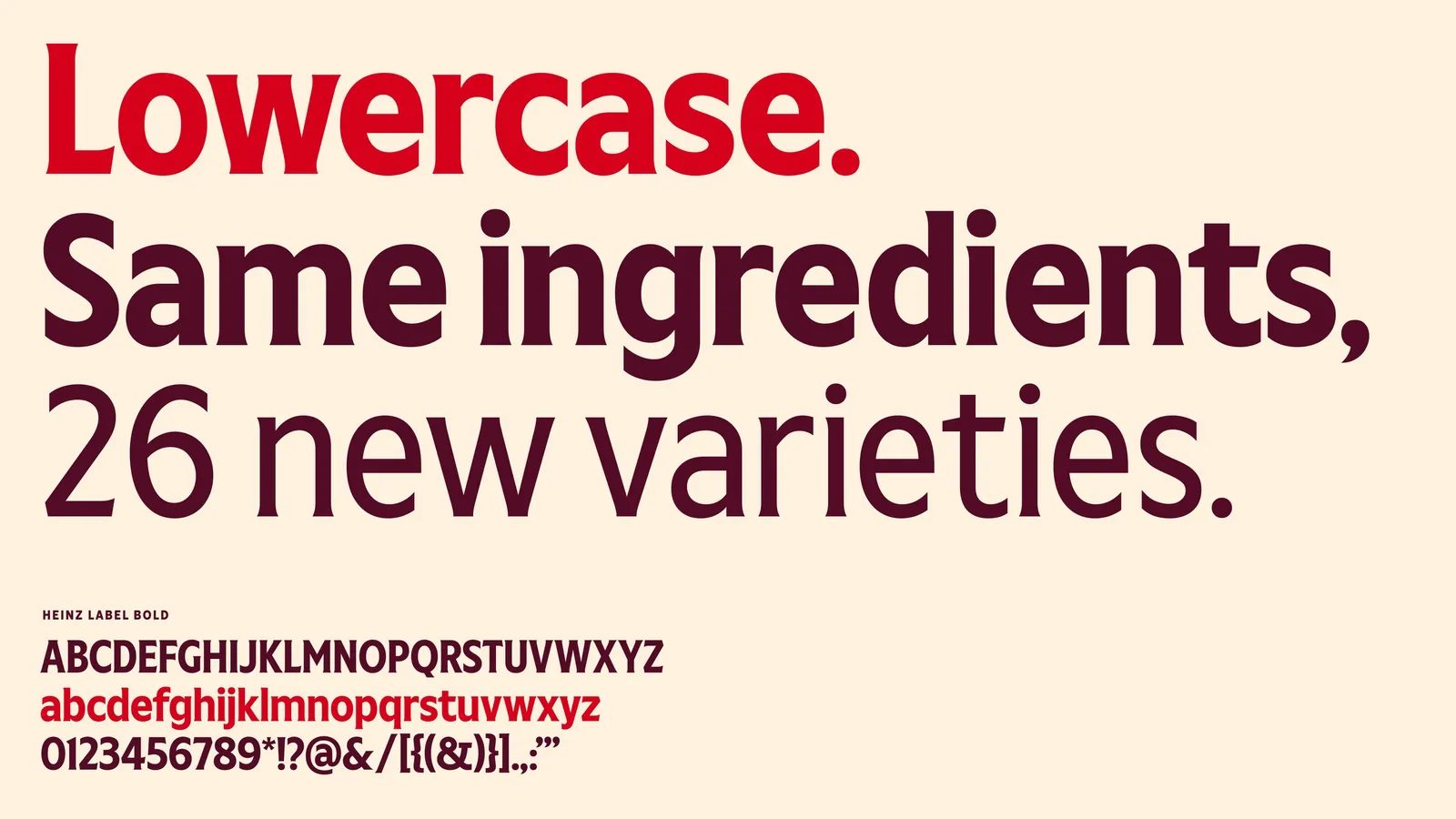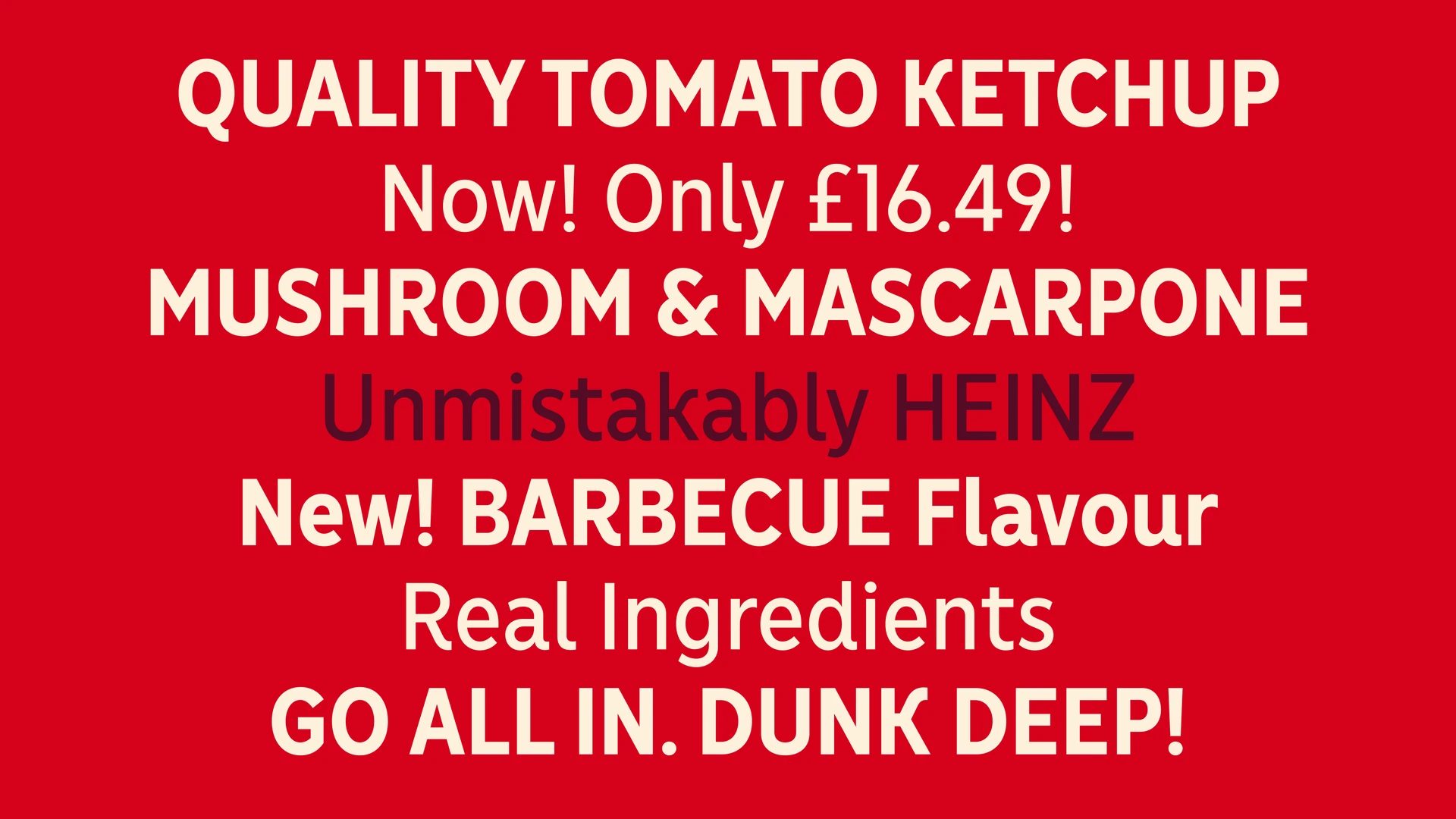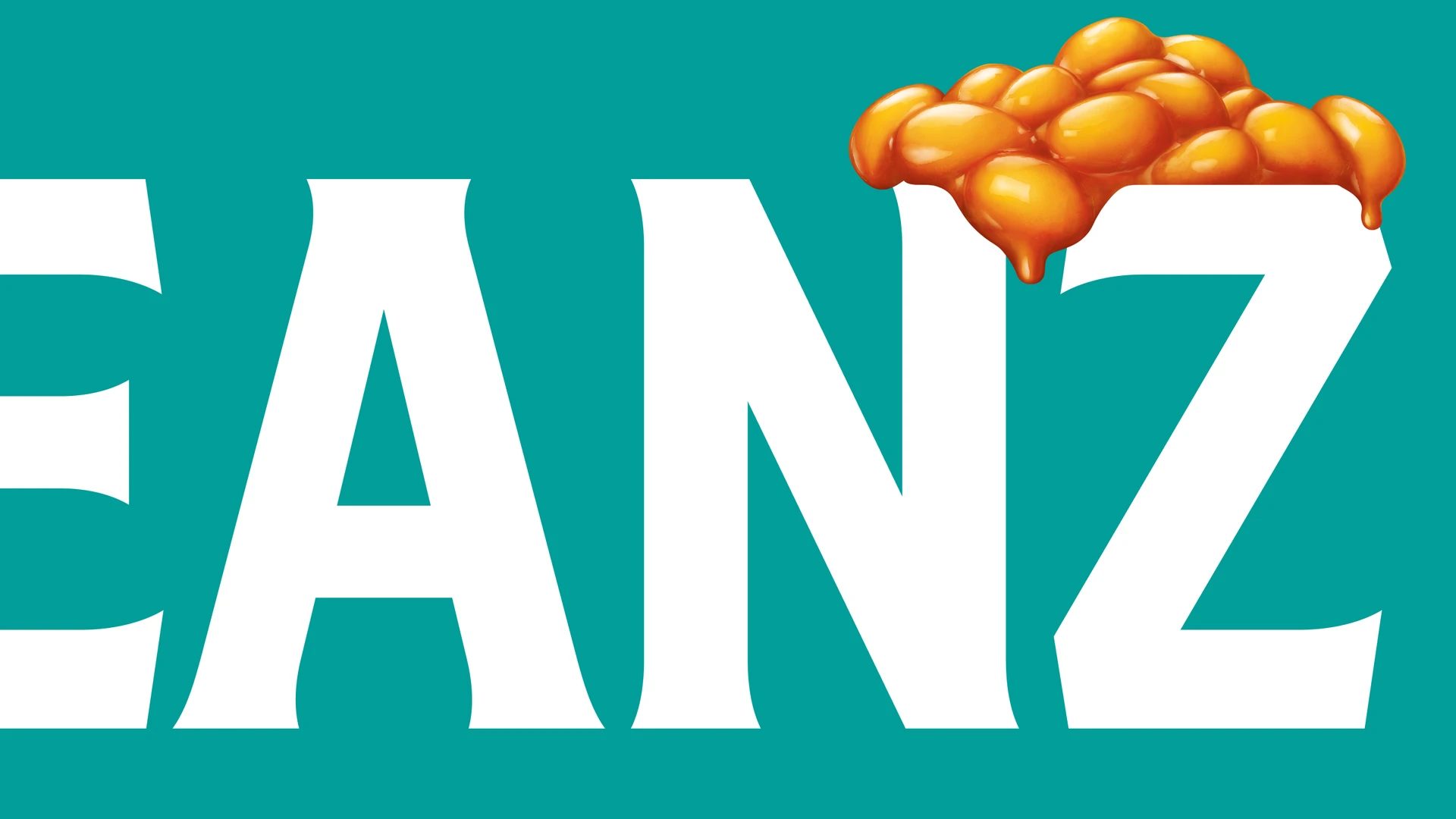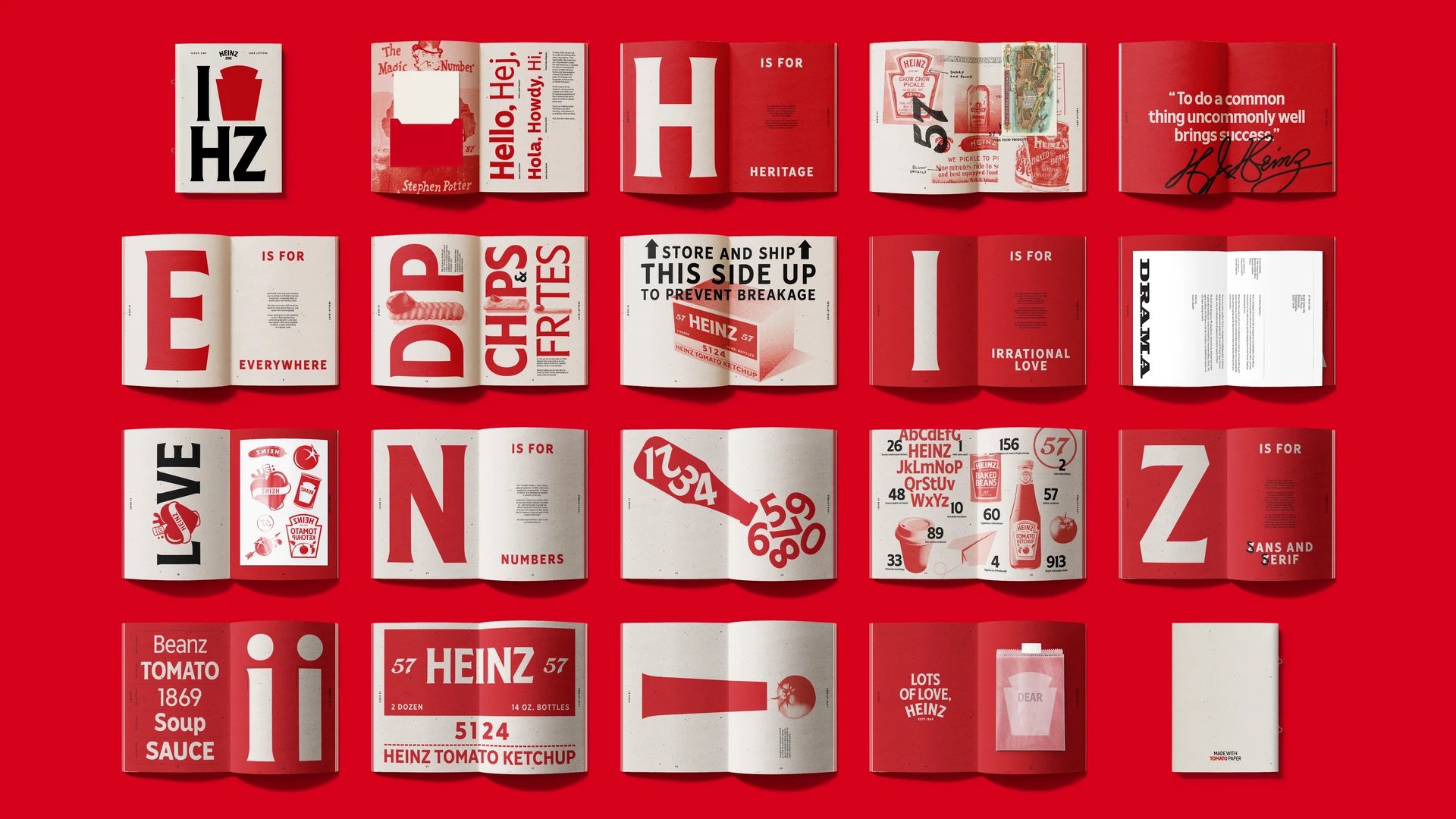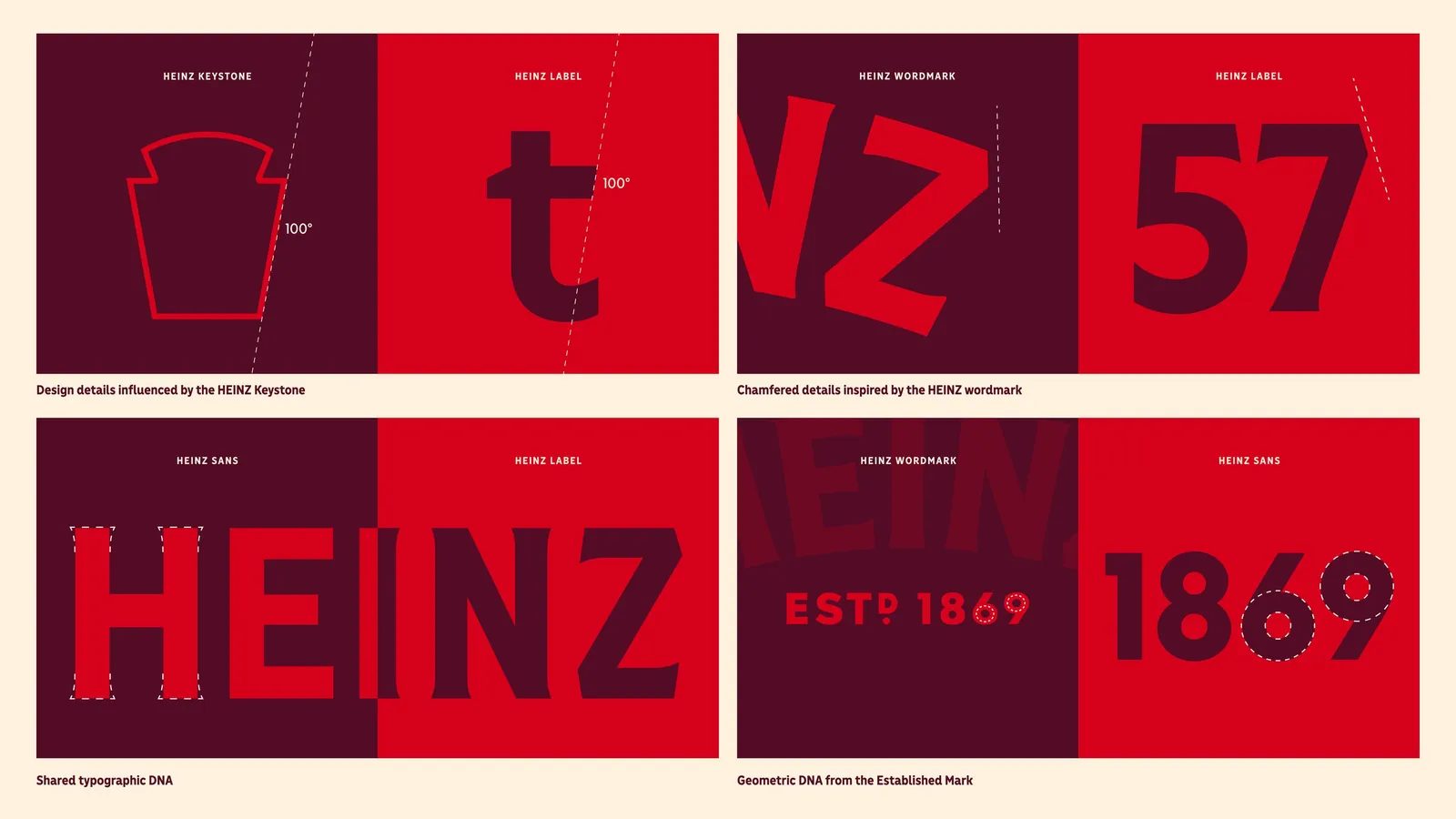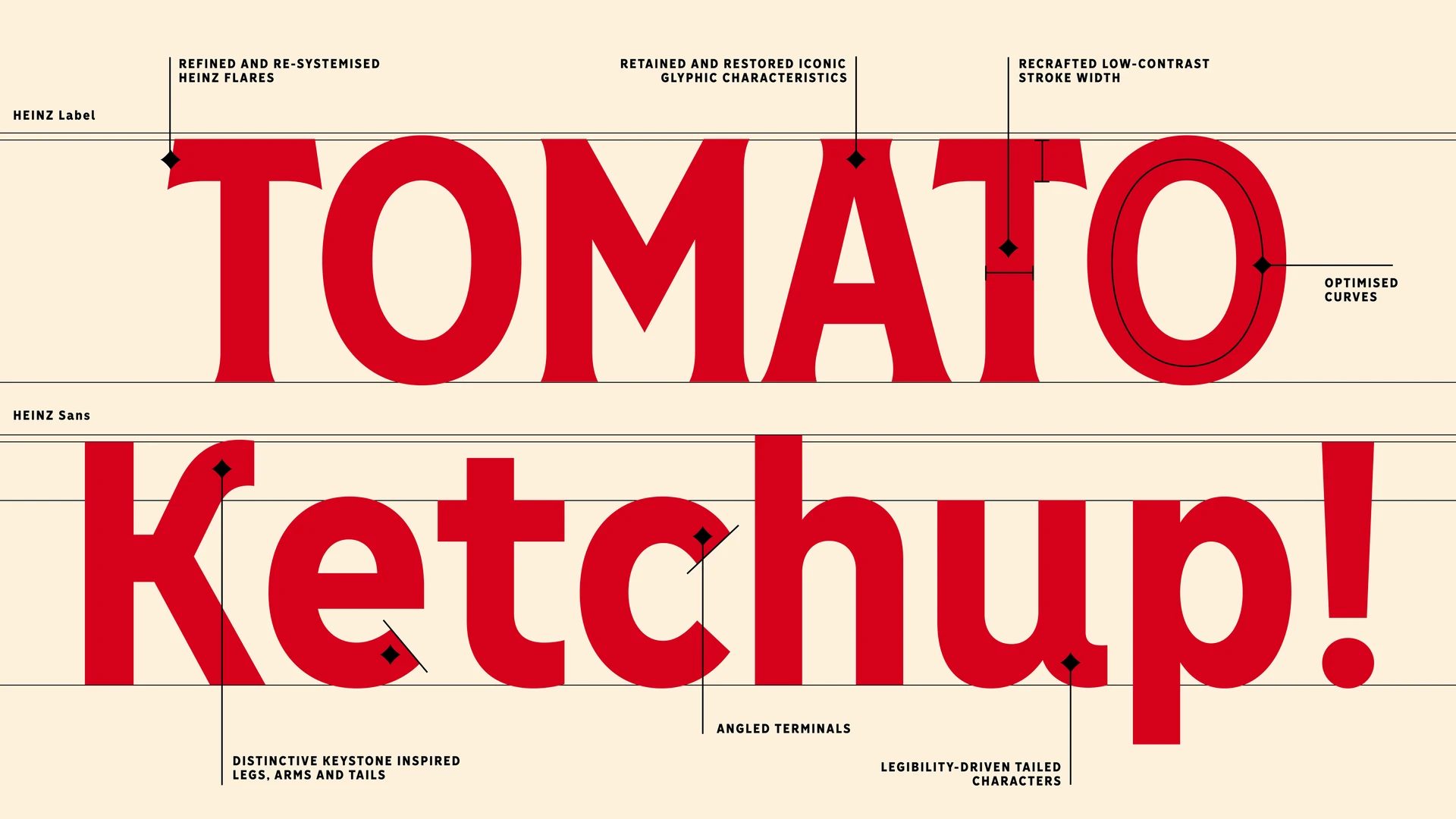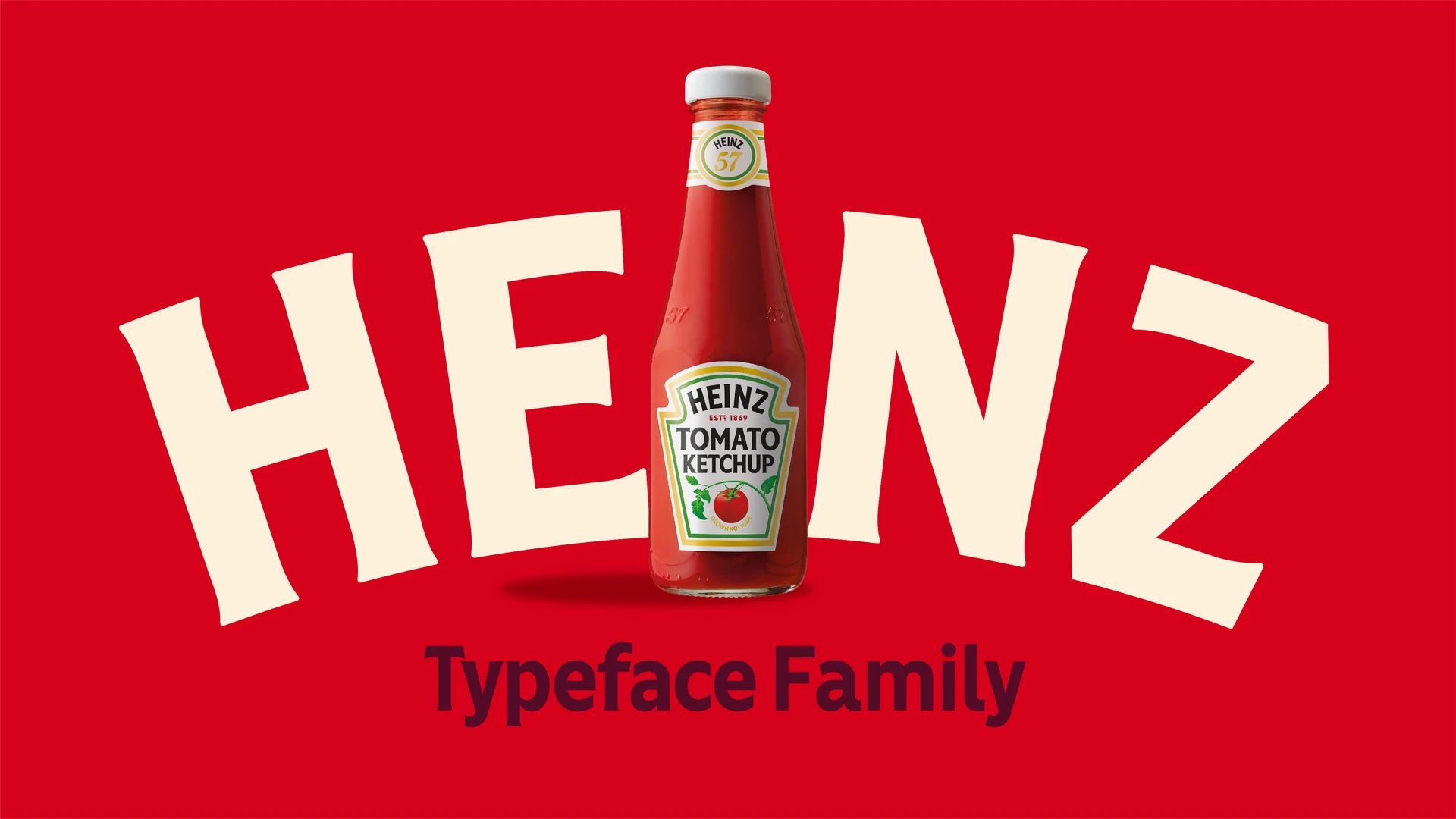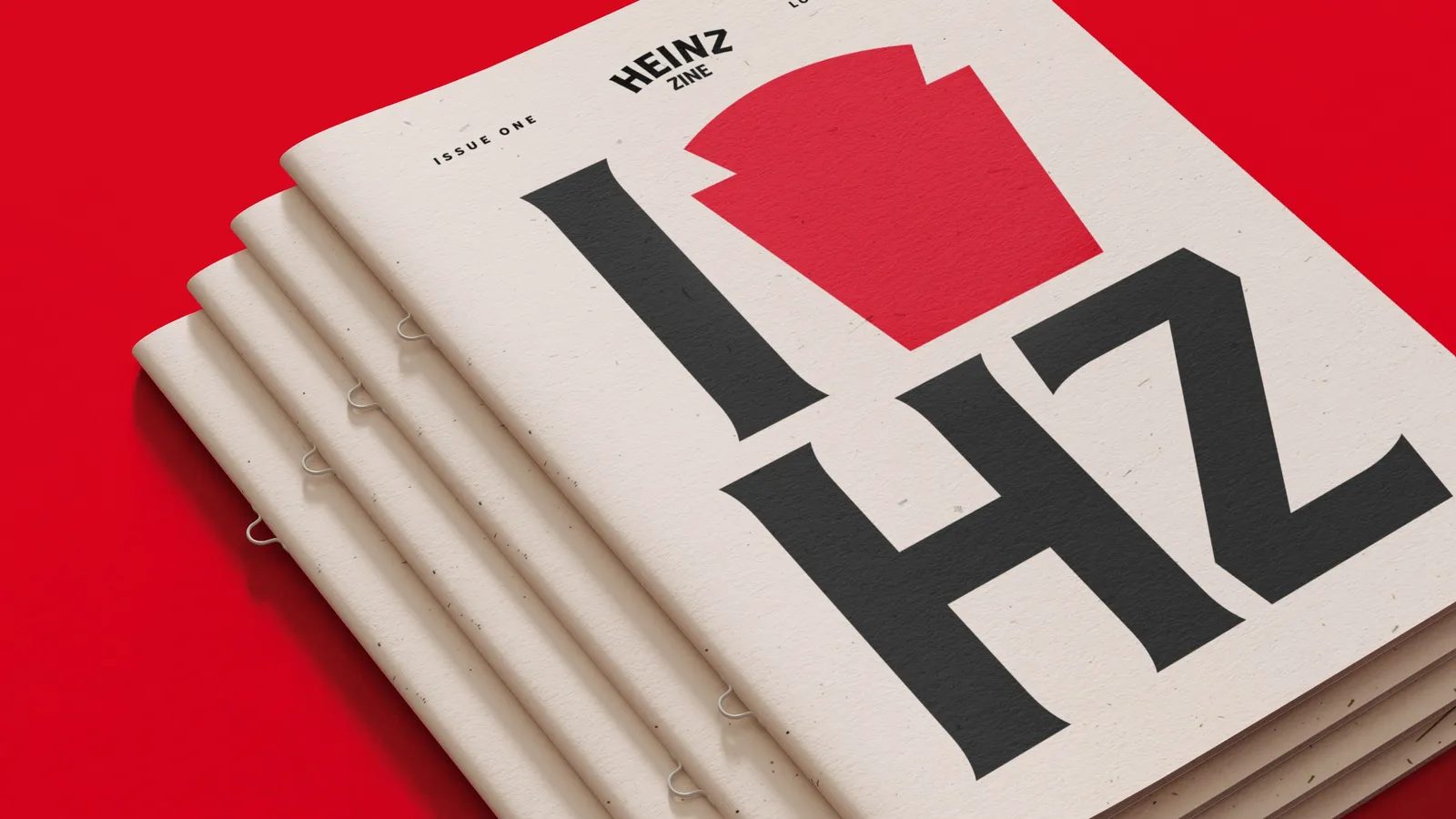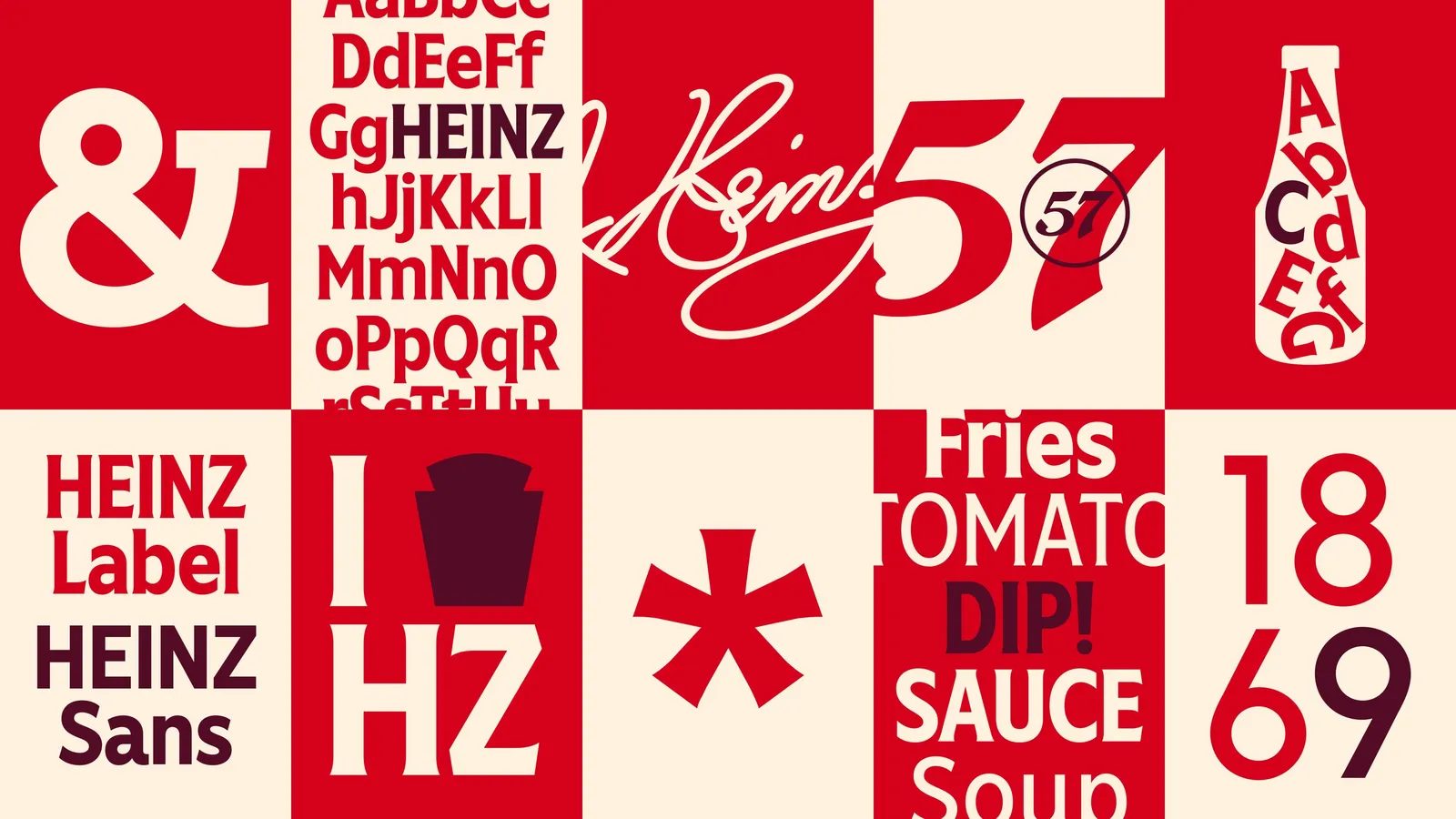
Disseny gràfic destacat de la setmana: Heinz Typeface by Studio Drama
Una tipografia a mida que reforça un dels sistemes de marca més reconeixibles del món
Quan una marca porta més de 150 anys formant part de la cultura popular global, qualsevol intervenció en la seva identitat visual ha de ser d’una precisió gairebé quirúrgica. El projecte Heinz Typeface, desenvolupat per Jones Knowles Ritchie juntament amb Studio DRAMA per a Kraft Heinz, és un exemple magistral de com el disseny tipogràfic pot preservar un llegat icònic i, alhora, adaptar-lo a les necessitats actuals. Guardonat amb un D&AD Wood Pencil 2025, aquest projecte demostra que la tipografia continua sent un dels actius estratègics més potents dins del branding global.
Preservar i evolucionar: el punt de partida
L’origen del projecte parteix d’una realitat habitual en marques històriques: amb el temps, l’ús acumulat del wordmark i diferents alfabets havia generat inconsistències. Les icòniques majúscules de Heinz, reconegudes arreu del món, requerien una revisió profunda per recuperar ritme, coherència i claredat.
En comptes de reinventar la marca, l’equip va optar per una evolució silenciosa. Cada corba, angle i terminal es va redibuixar amb cura per mantenir intacta la personalitat atrevida de Heinz, però adaptant-la als estàndards tipogràfics actuals. És una feina que no busca protagonisme, però que transforma de manera substancial la percepció global de la marca.
La tipografia com a nucli del reconeixement global
Des de Ketchup i Beanz fins a Mayo o Cream of Tomato, Heinz és una presència constant als supermercats d’arreu del món. En aquest ecosistema visual tan ampli, la tipografia esdevé un element cohesionador fonamental.
Heinz Typeface es va desenvolupar alineant cada lletra amb els elements més distintius de l’univers visual de la marca: el keystone, la forma de l’etiqueta, el wordmark històric i el seu ritme característic. Aquesta coherència permet que la tipografia actuï com a fil conductor visual en un sistema que abasta milers d’aplicacions, idiomes i contextos culturals.
Unmistakably Heinz: lletres amb ADN propi
Un dels grans èxits del projecte és que cada lletra és reconeixible fins i tot per separat. El ritme del wordmark original va servir de guia, assegurant que el caràcter Heinz fos present en cada glif.
El keystone —símbol històric de la marca— va influir directament en angles, talls i corbes, generant una coherència formal que travessa tot el sistema tipogràfic. El resultat és una veu visual tan única com el gust de Heinz: difícil de definir, impossible de confondre.
Aquest nivell de “propietat” és un dels grans objectius del disseny tipogràfic contemporani aplicat al branding.
Label: una nova dimensió expressiva
Un dels grans avenços del projecte és l’ampliació del tipus original amb una nova minúscula, numeració i signes de puntuació. Per primer cop a la seva història, Heinz disposa d’una tipografia completa capaç de modular el to de la seva comunicació.